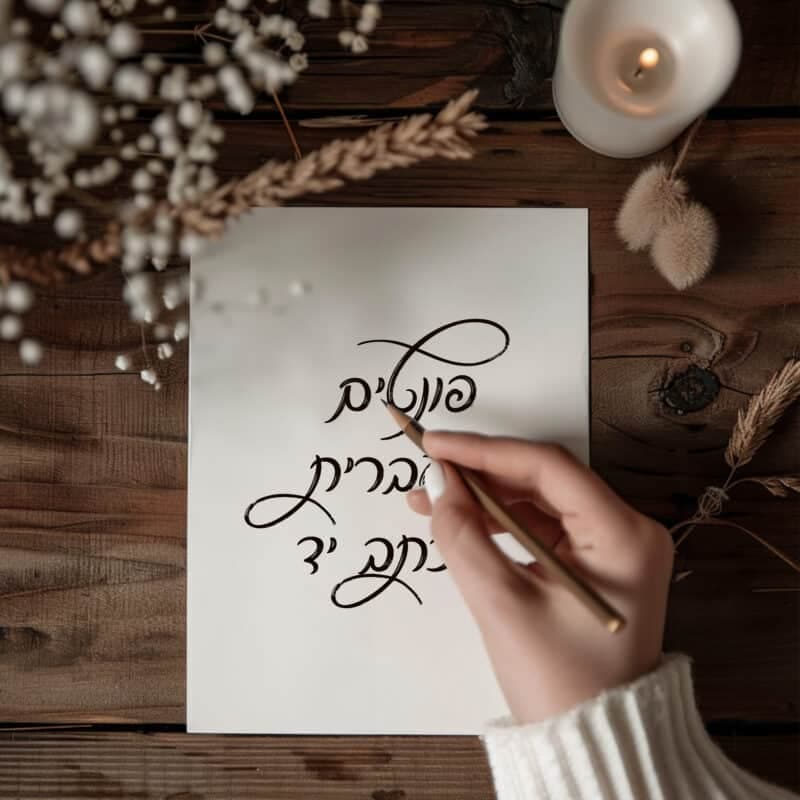
בעולם שבו המינימליזם והסנס סריף שולטים במרחב הדיגיטלי, פונטים בכתב יד מציעים ניגוד מרענן ואותנטי. הם מכניסים טאצ׳ של חום אנושי שהרבה פעמים קצת חסר בעיצובים המודרניים והנקיים וזה מה שמעניק להם כוח להדגיש ולהבליט כל מסר בצורה אישית ומושכת.
פונטים אלו נתפסים לעיתים קרובות כפחות מקצועיים או פחות רציניים, אבל אולי הגיע הזמן לשנות את הדעה הזו? הרי כשמדובר בלוגואים ועיצובים פרסומיים, פונטי כתב יד הוכיחו את עצמם ככלי עוצמתי ליצירת קשר רגשי ואמיתי עם הקהל.
פונטים בעברית כתב יד לא רק נראים טוב, יש להם השפעה חזקה על קליטת המידע וההתחברות הרגשית של הקוראים. מחקרים מצביעים על כך שהם יכולים לשפר את הבנת הקורא בכ-20%, בזכות הדרישה לקריאה מעמיקה יותר שהם יוצרים.
כשבוחרים לעבוד עם פונטים כתב יד בעברית, חשוב לזכור שהשימוש בהם צריך להיות מבוקר ומושקל. פונטים אלו מתאימים במיוחד לכותרות, ציטוטים או כל טקסט שרוצים להדגיש ולהבליט. הם יכולים לתת מראה נפלא לאתרים, כרזות, וחומרי פרסום שונים.
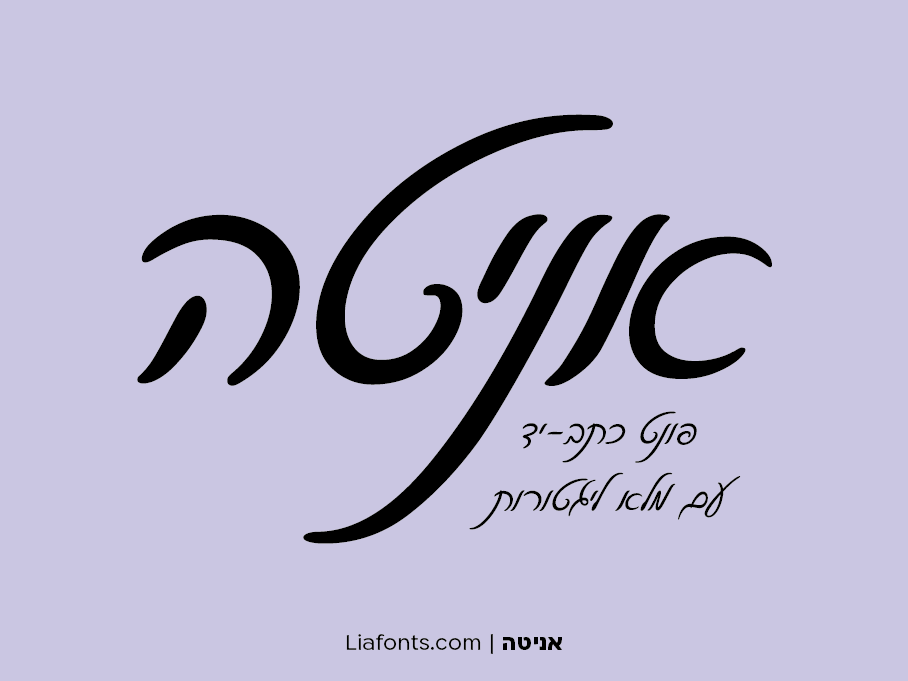
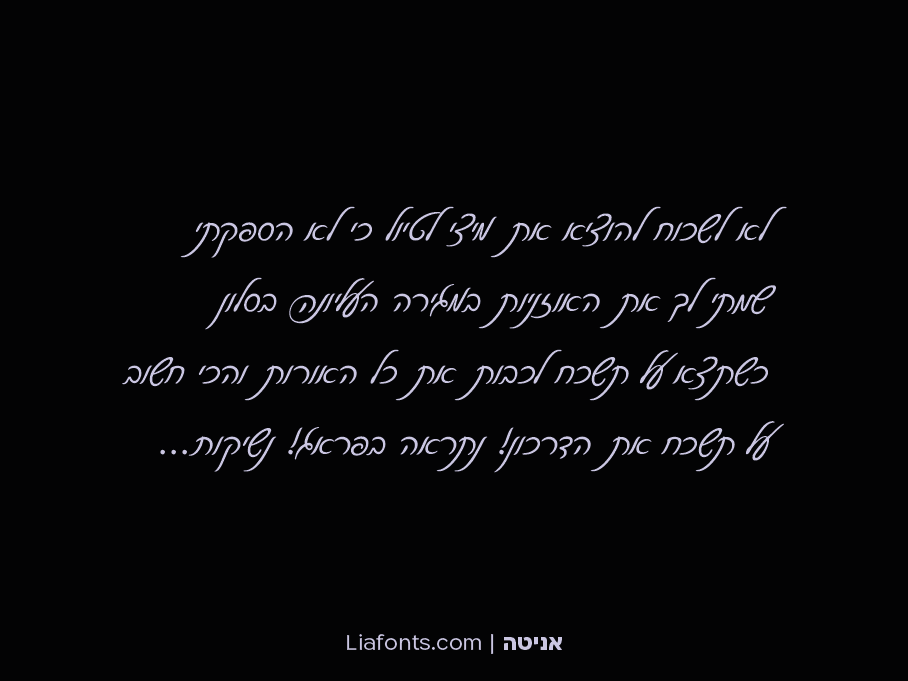
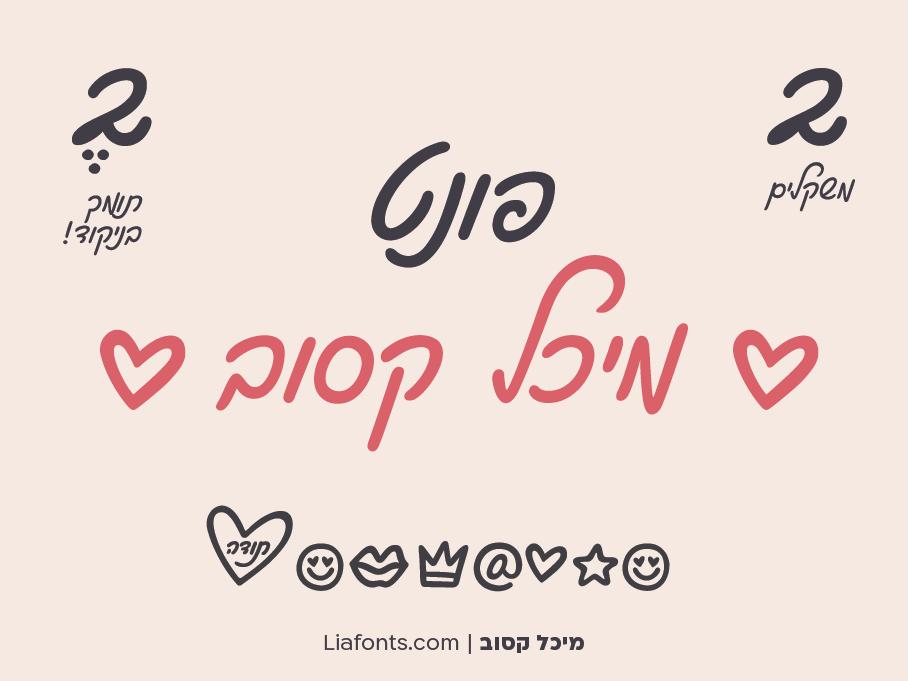
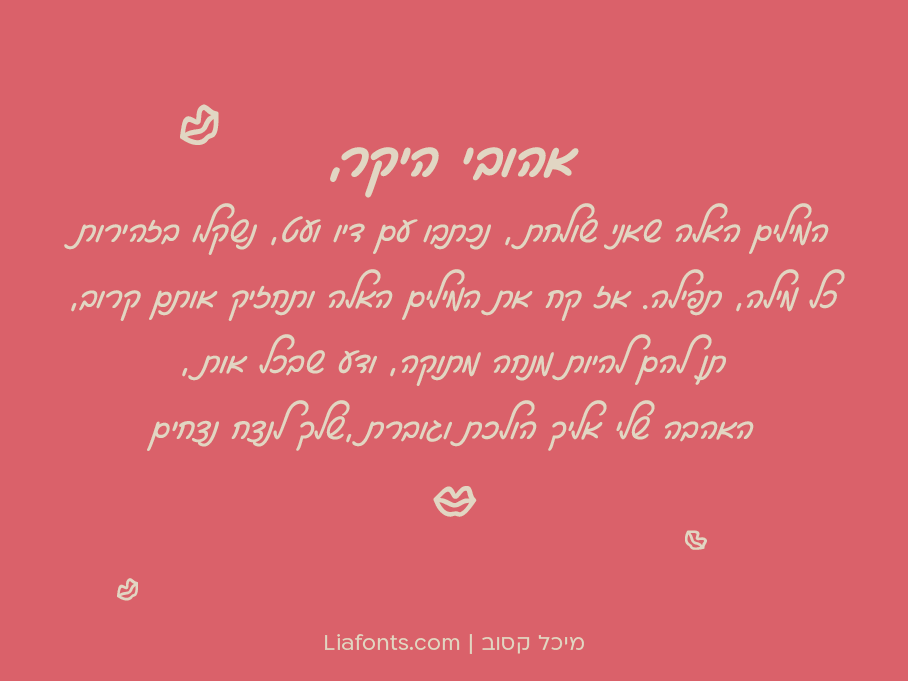
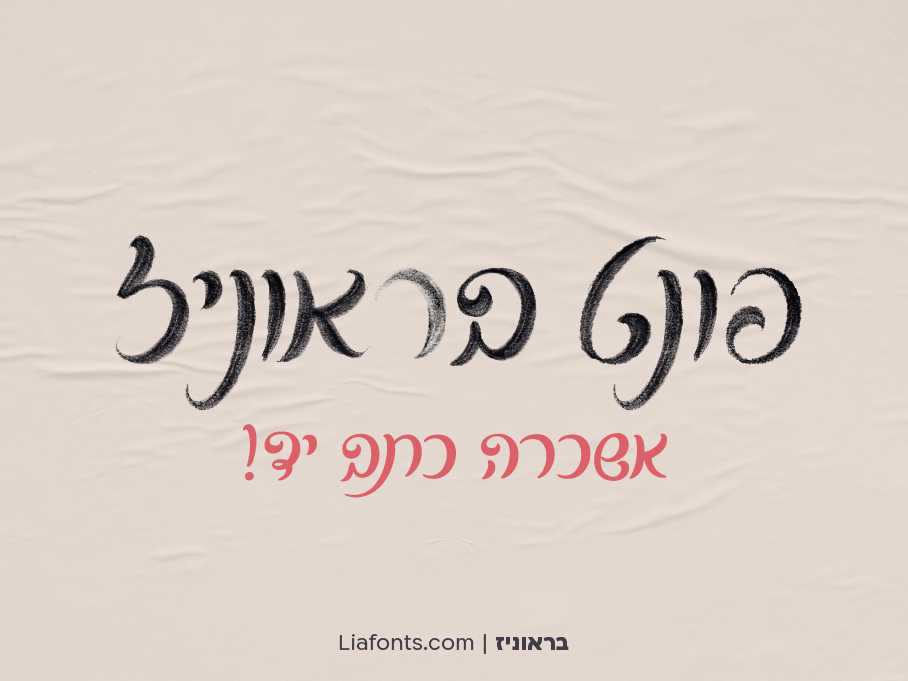
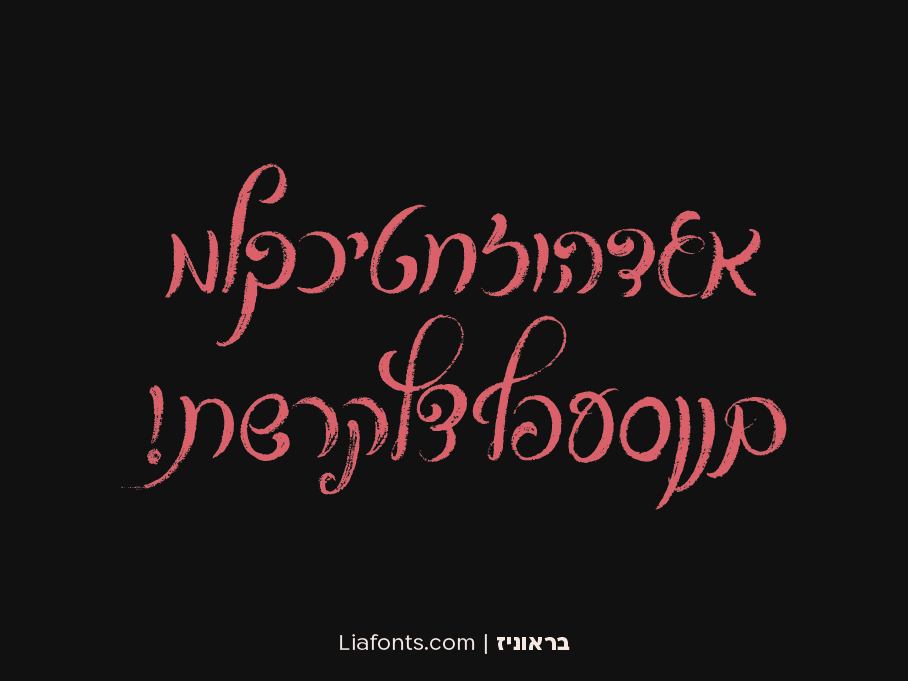
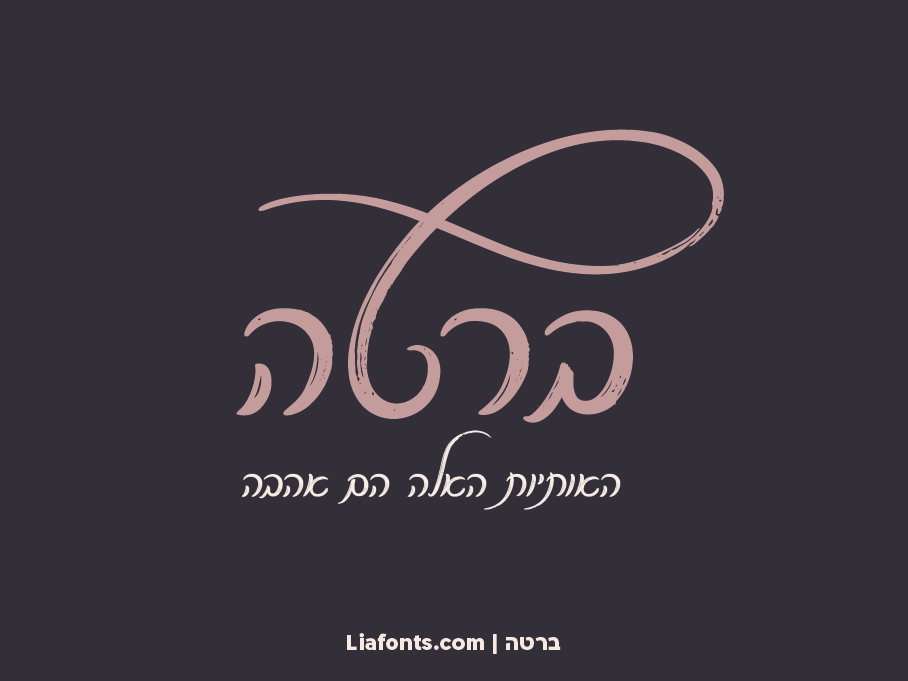
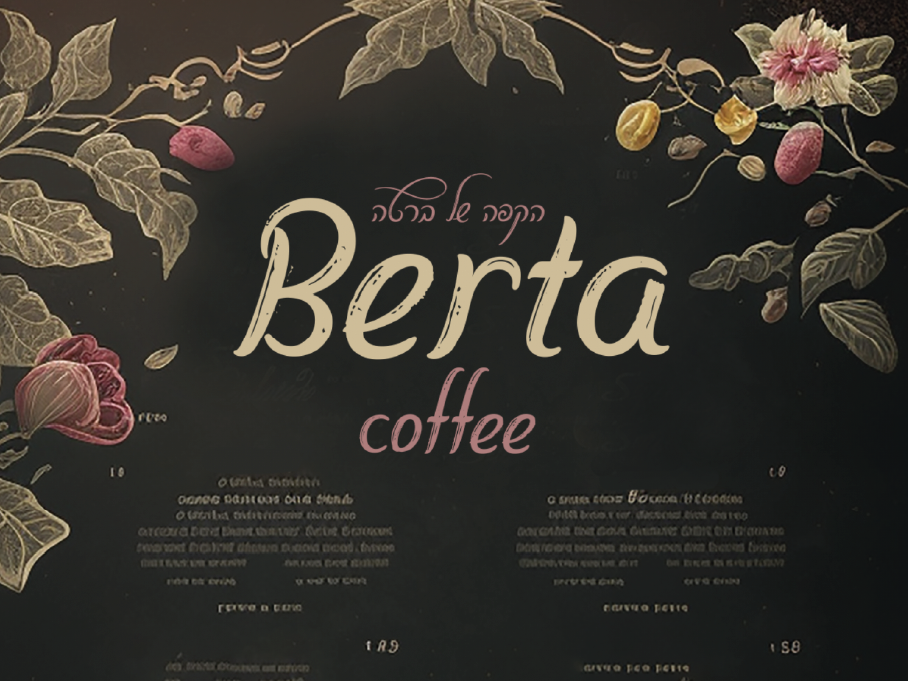
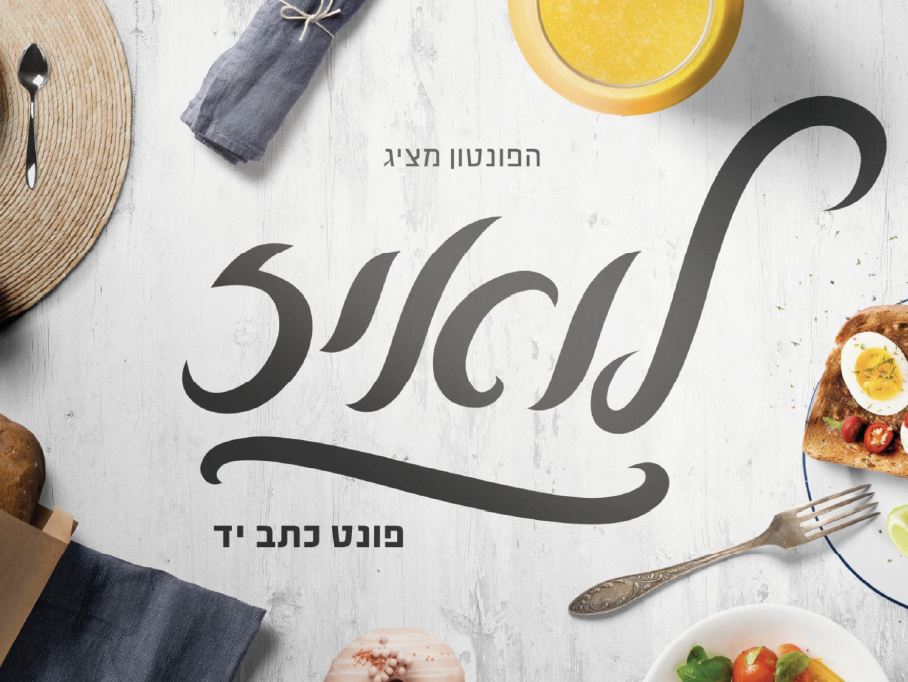
רוב הפונטים בכתב יד מתאימים להדפסה, אך יש לבדוק את איכות הפונט בגודל קטן או בפורמטים שונים, כמו דפוס או הדפסה על נייר.
הבחירה בפונט תלויה במטרה של העיצוב. חשוב לבחור פונט שמתאים לאופי המסר – פונט רך ועדין יתאים להזמנות, ואילו פונט גס יותר עשוי להתאים לכותרות או פוסטרים.